Les changements de période sont toujours propices aux bilans et aux nouvelles (bonnes) résolutions. Se fixer des objectifs pour la nouvelle année : bateau ? banal ? Pourquoi pas, mais que ce soit pour la nouvelle année ou toute autre occasion, il est parfois bénéfique de prendre un peu de recul et de faire le point sur ses envies.
2017 a été une année assez intense, notamment avec la création du blog qui n’était pas vraiment prévue. Créer Lettres & Co a été une belle aventure – je passe les petites galères techniques et autres grands questionnements. Le blog démarre fort à ma grande surprise. Et à ma grande joie aussi, car c’est un investissement personnel important, et j’aurais été désolée de n’avoir pour lecteurs que ma maman et mes copines, même si leur soutien est inestimable.
Lettres & Co, c’est avant tout le partage d’un cheminement, d’un savoir-faire en construction, d’inspirations et de petits conseils pour progresser. Aujourd’hui, je partage avec vous mes envies pour la nouvelle année. Comme chaque année, j’essaie de les mettre en forme de façon à pouvoir les afficher au dessus de mon bureau, comme un pensum.
Les objectifs artistiques de l’année 2018
Aller à l’essentiel
Ce petit « mantra » me hante depuis qu’il m’a été susurré lors d’un stage fin novembre. Aller à l’essentiel, ce n’est pas épurer ou élaguer. C’est se concentrer sur la substance, et s’affranchir des fioritures, car on en a pas besoin. Un bel objectif, surtout pour moi qui ait tendance à rajouter un peu de ceci, un peu de cela… Plus qu’un objectif, un défi en fait !
2. Raconter un jardin poétique, extraordinaire et luxuriant
Dans la lignée de 2017, le végétal va peupler voire envahir mes travaux. A la manière des enlumineurs, me direz-vous, mais de façon plus contemporaine, même si l’enluminure est pour moi une source d’inspiration importante. Dans la continuité du stage « Lettres et Fleurs » et de mes travaux d’illustration, je vais poursuivre la recherche, créer le foisonnement, asseoir un beau répertoire de formes. Ce jardin sera poétique et extraordinaire, je l’espère ! Vous y croiserez peut-être quelques créatures sorties d’on ne sait où…
Plus que jamais, j’ai envie de raconter des histoires
3. Magnifier l’écriture dans sa simplicité
Une jolie phrase pour dire que je vais continuer de perfectionner les écritures que je pratique déjà régulièrement. Pas d’envie particulière d’en apprendre une nouvelle, mais plutôt l’objectif de faire mieux, de travailler la pureté du trait et l’expressivité.
4. Travailler le geste, la composition, l’énergie
En continuité du point 3., le point 4 vise à faire des trucs très complexes, mais que les personnes qui le voient ne s’en rendent pas compte . Vous me suivez ? En fait, je trouve toujours qu’il y a un petit quelque chose de pas naturel, de bancal dans mes compos ou dans mon écriture. L’idée ici c’est un peu l’idée du nombre d’or : que le résultat soit évident, que ça aille de soit. J’aime aussi l’idée de l’énergie, du mouvement : à voir comment exploiter tout ça !
Pour mettre en application ces points 3 et 4, je pense travailler avec les haïkus, ces petits poèmes japonais qui en 3 vers sont un concentré de poésie, de vie et… d’efficacité !
Je vais aussi travailler abondamment la gestuelle, au tire-ligne et à la plume fine.
5. Célébrer l’enfance, la nature, l’imagination et le merveilleux
C’est peut-être l’époque ou l’âge ou les deux : seule à ma table de dessin, je veux décoller, rêver, partir, revisiter de bonnes sensations. Au travers de la poésie de Bobin, d’Anna de Noailles, de Prévert, de Bashô, ou dans des petits tableaux sans texte, dans des linogravures, des cartes, on verra. J’aimerais aussi illustrer un petit conte.
6. Faire de belles rencontres artistiques et toujours… partager !
Que ce soient des rencontres sur la toile (notamment Instagram) ou dans la vraie vie, je dois dire que le talent des autres m’inspire énormément. J’aime admirer leurs travaux, j’aime échanger les petits secrets de fabrication, j’aime discuter des astuces… Concrètement, je vais bien sûr continuer d’être très présente sur Instagram et faire au moins un stage dans les 6 prochains mois pour découvrir de nouvelles choses. Moi qui ait travaillé très seule pendant des années (c’est là que vous sortez votre petit mouchoir, merci), je ne sais pas comment vous dire à quel point il est fondamental de partager pour progresser. Montrer son travail, se confronter aux autres, échanger, rire, parler des projets, s’ouvrir sur le monde.
De nouvelles rencontres, ce seront aussi, peut-être, j’espère, de nouvelles collaborations…
Partager, ce sera au travers de Lettres & Co, évidemment. Toutes ces envies vont se matérialiser peu à peu dans des créations et différents projets. J’ai bien sûr prévu de partager tout cela avec vous, dans des tutos ou des pages de découvertes. J’espère que le credo poétique, végétal et merveilleux vous inspire !
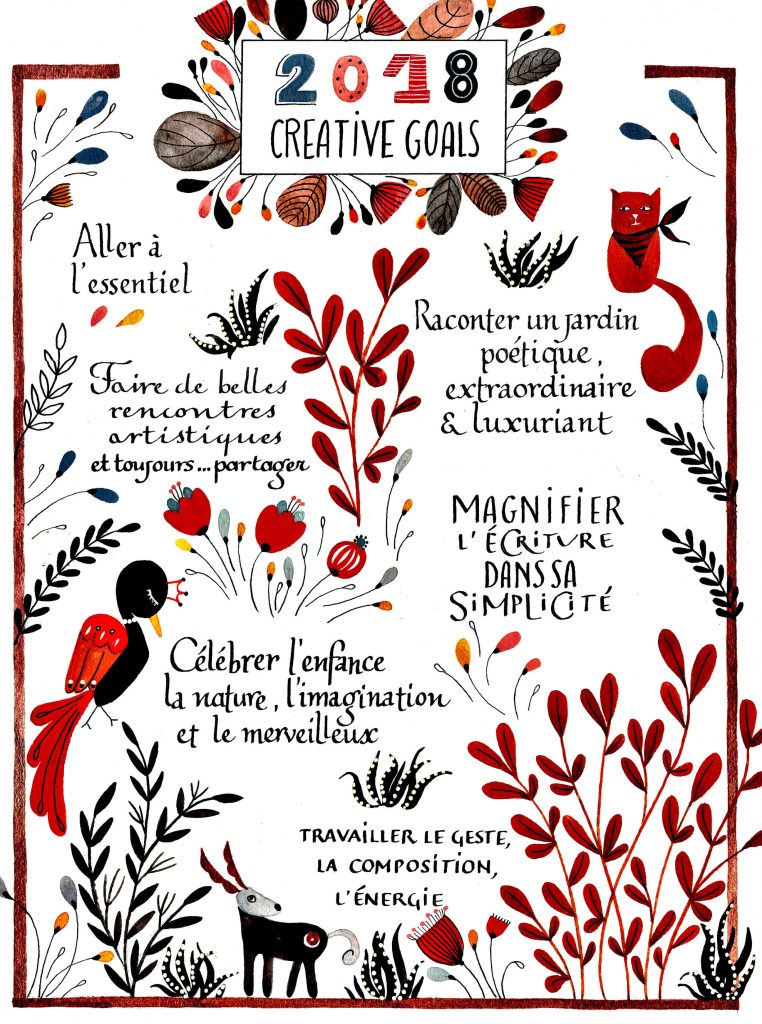
Voilà, 2018 c’est parti ! Avez-vous défini vos objectifs artistiques ? N’hésitez pas à partager dans les commentaires !